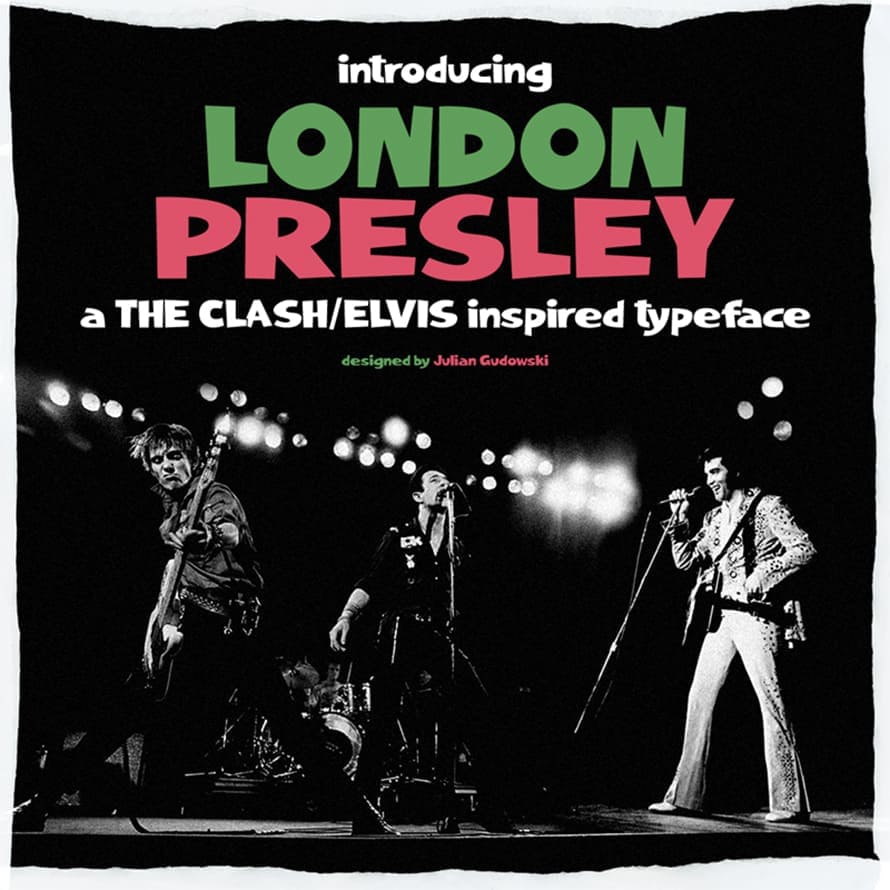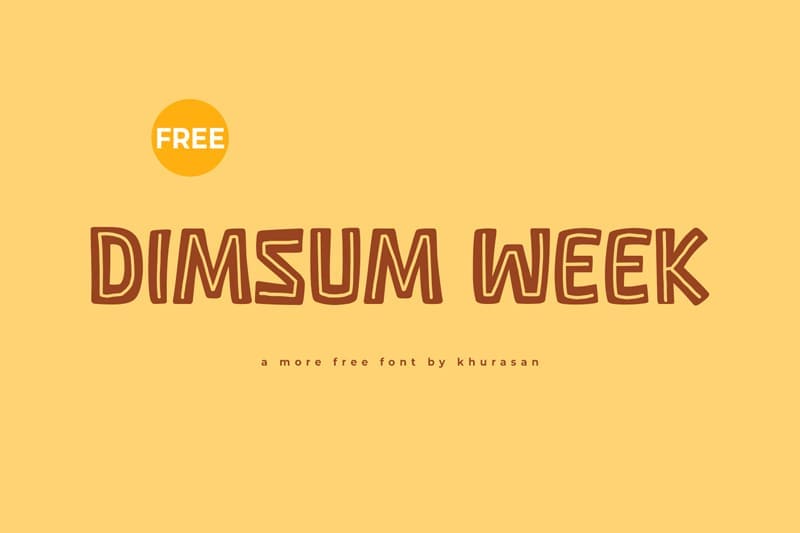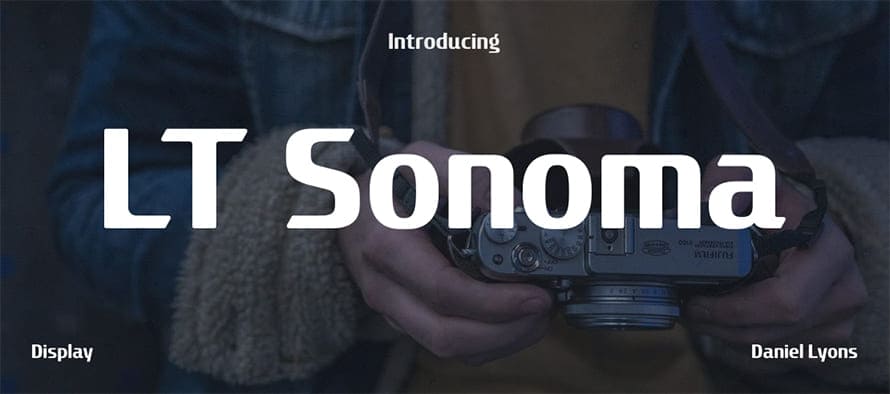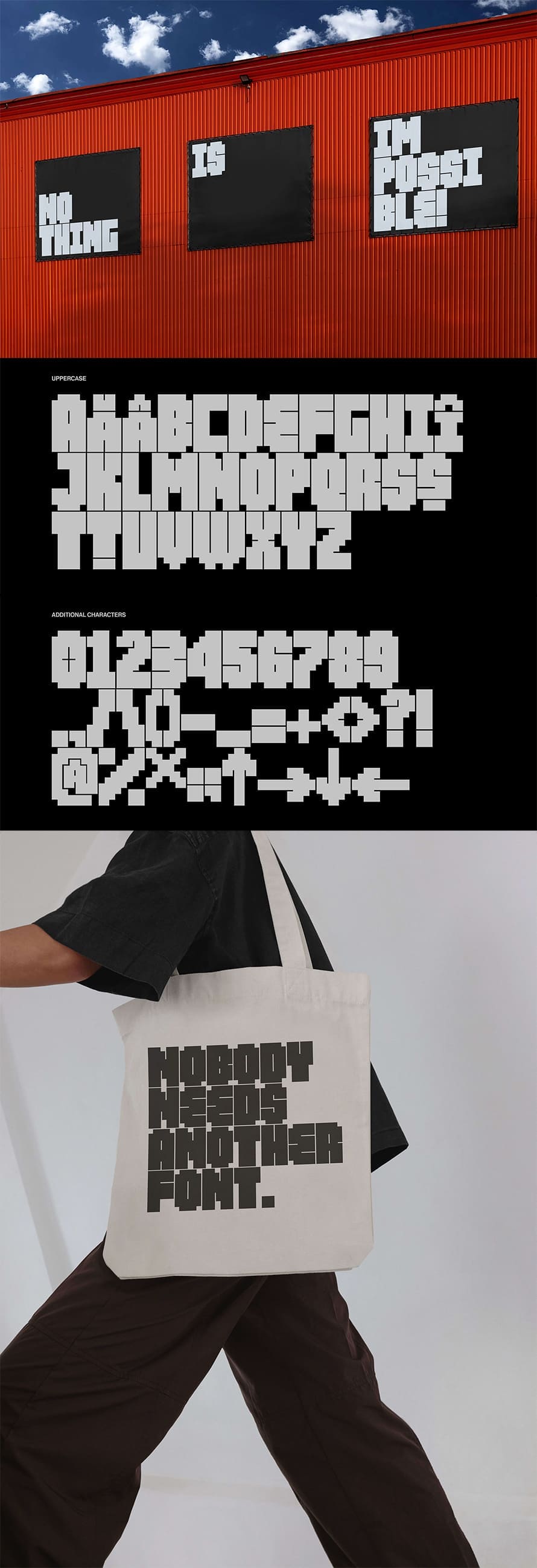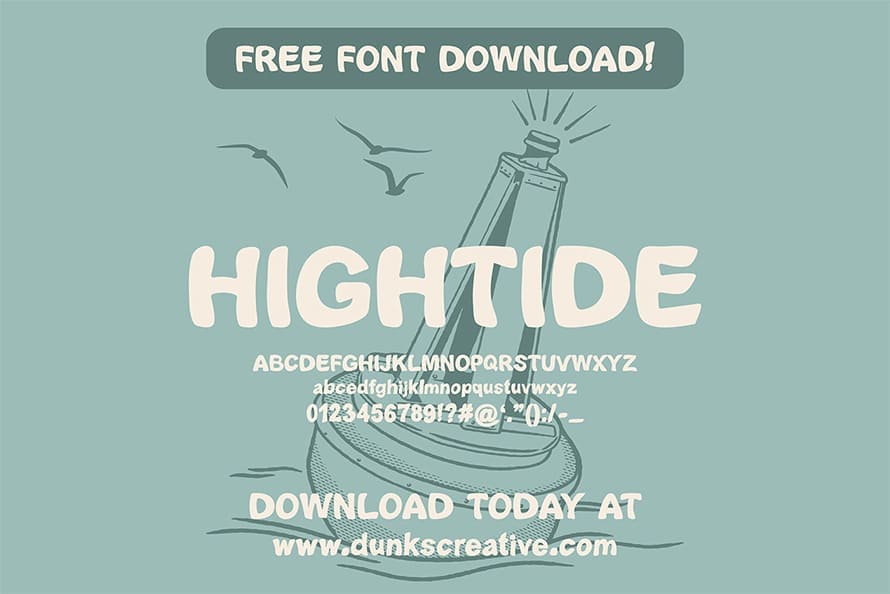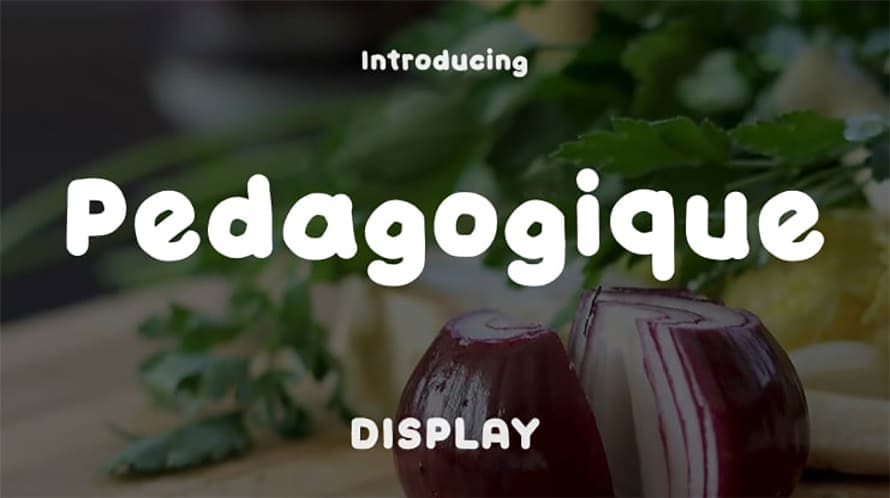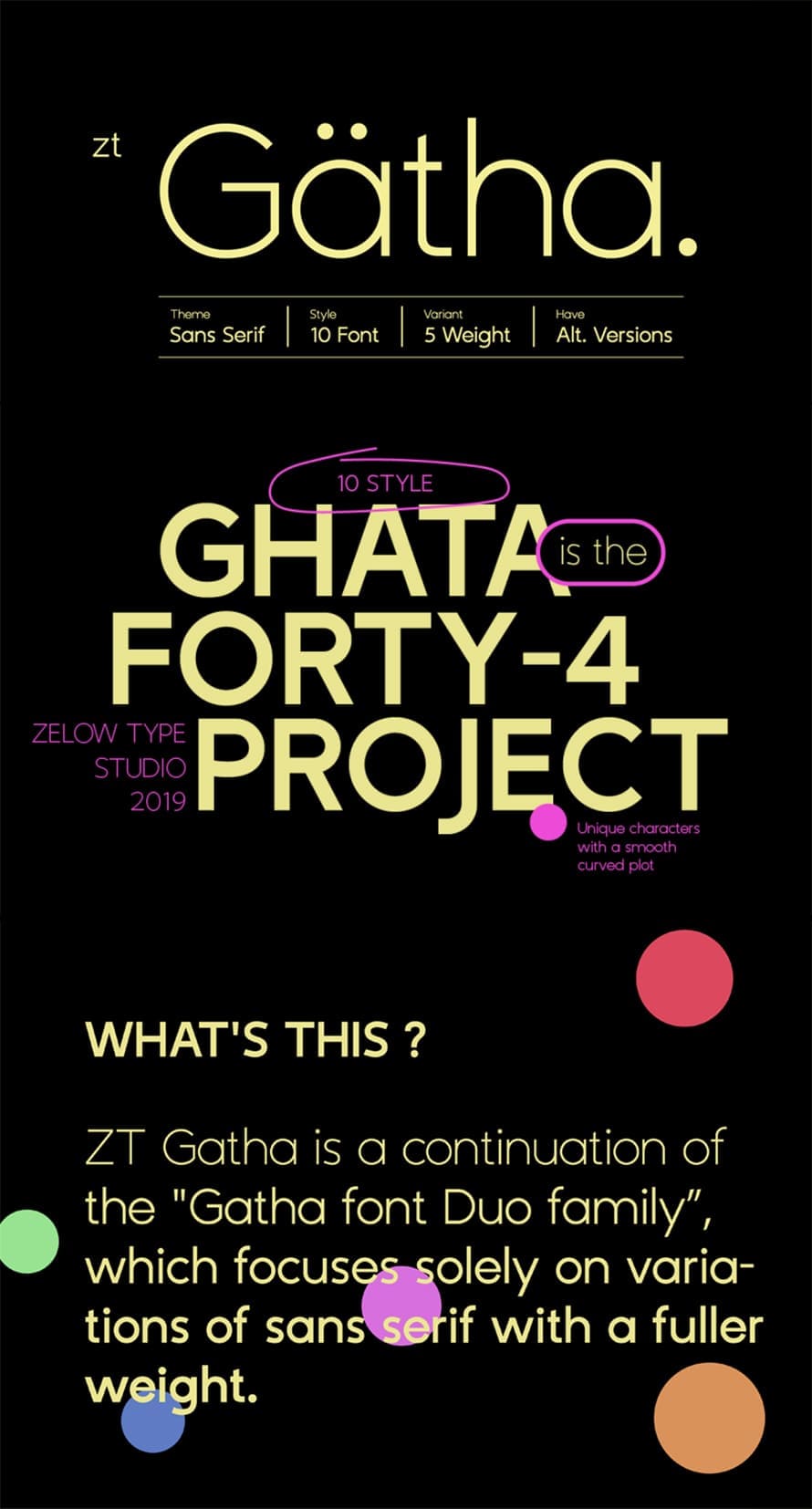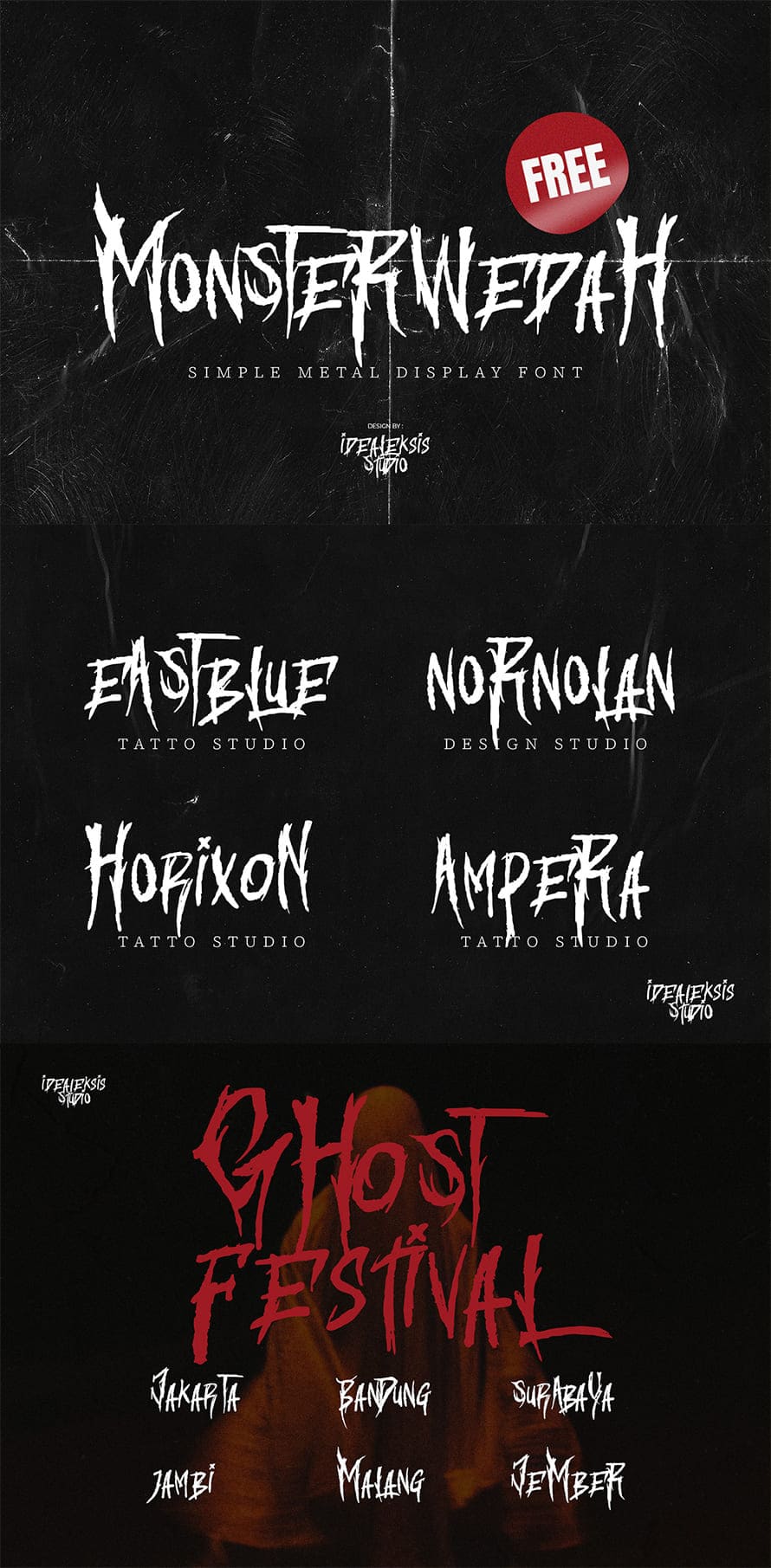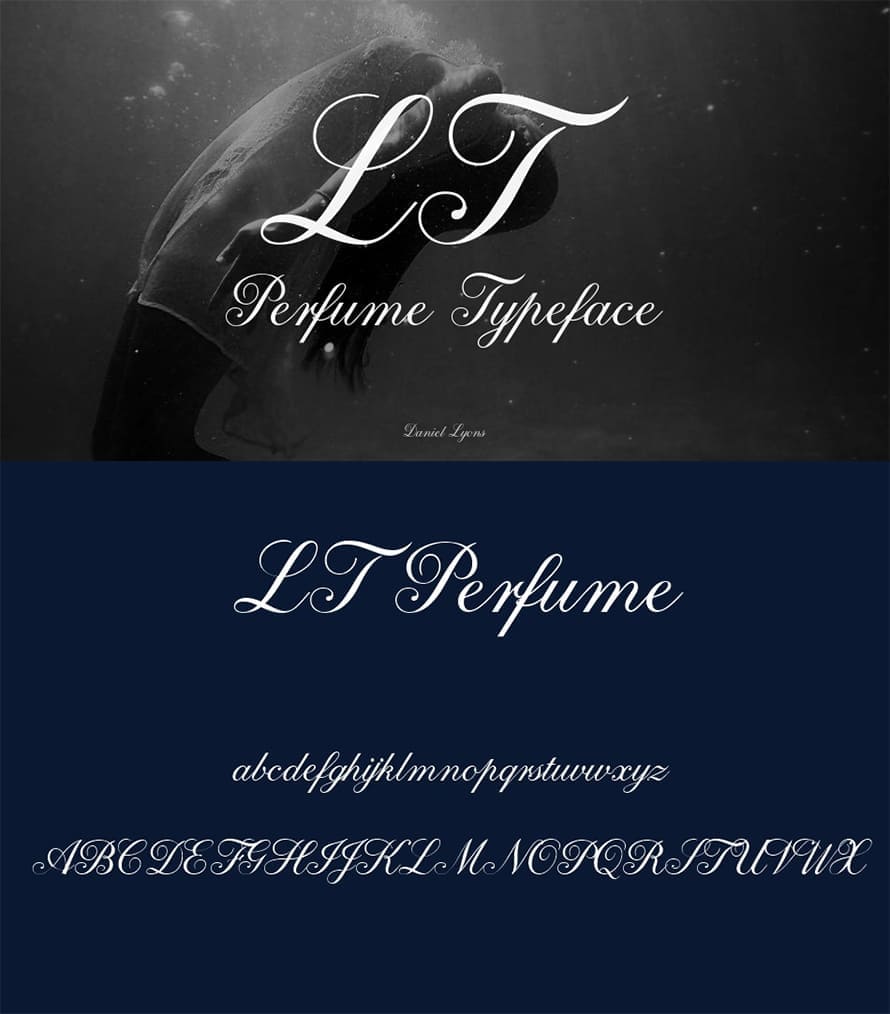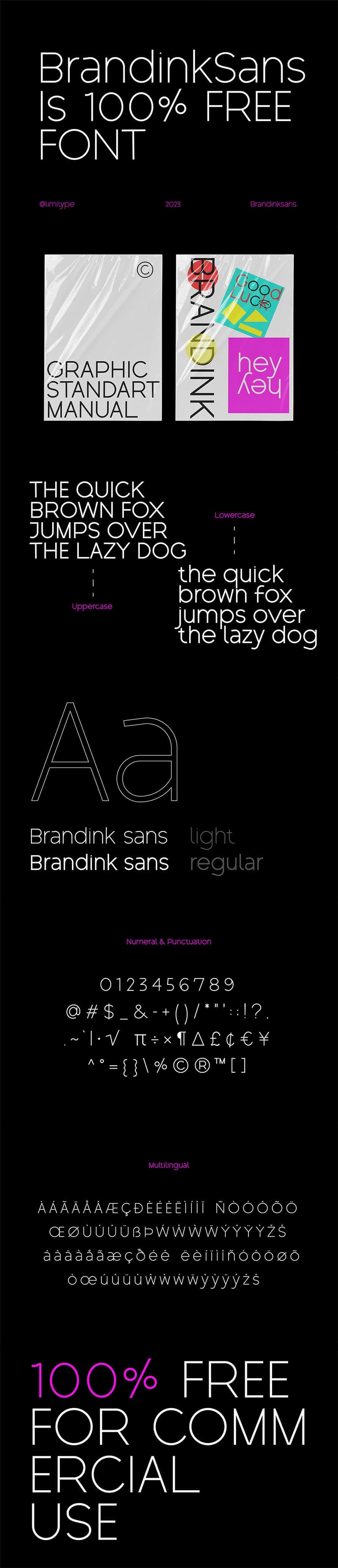
25+ Free Fonts für Designprojekte
In der Welt des Grafikdesigns ist die Suche nach frischen Schriftarten endlos. Designer, sowohl erfahrene als auch Anfänger, sind ständig auf der Suche nach neuen kostenlosen Schriftarten, um ihren Projekten Vitalität zu verleihen. Die Bedeutung der Typografie bei der Übermittlung von Botschaften, beim Hervorrufen von Emotionen und beim Aufbau einer Markenidentität ist nicht zu überschätzen. Daher hat die Verfügbarkeit hochwertiger, kostenloser Schriftarten einen immensen Wert für Designer weltweit.
In diesem Artikel begeben wir uns auf eine Reise, um zu erkunden, wie die Integration der neuesten kostenlosen Schriftarten Ihre Designs zu neuen Höhen der Kreativität und Wirkung führen kann.
Sie befinden sich mitten in einem Designprojekt und suchen nach der perfekten Schriftart, um die Essenz Ihres Konzepts einzufangen. Die Suche beginnt damit, unzählige Schriftartenbibliotheken zu durchsuchen, in der Hoffnung, auf etwas zu stoßen, das mit Ihrer Vision übereinstimmt. Hier kommt die Magie neuer kostenloser Schriftarten ins Spiel. Diese Schriftarten, frisch geprägt von talentierten Designern und Typografen, bieten eine frische Brise inmitten des Ozeans von allgegenwärtigen Schriftarten.
Mit ihren einzigartigen Stilen, innovativen Funktionen und zeitgemäßen Ästhetik bringen neue kostenlose Schriftarten eine Prise Neuheit und Aufregung in Ihre Designvorhaben.
Liste der frischen Schriftarten:
Kreativität mit Vielfalt beflügeln
Als Designer gedeihen wir auf Inspiration, und nichts entfacht unsere Kreativität so sehr wie das Entdecken einer faszinierenden neuen kostenlosen Schriftart. Jede Schriftart erzählt eine Geschichte, die die kreative Vision und die akribische Handwerkskunst ihres Schöpfers widerspiegelt. Von schlanken serifenlosen Schriften bis hin zu eleganten Serifen, eigenartigen Display-Schriften bis hin zu vielseitigen Skript-Stilen – die Vielfalt neuer kostenloser Schriftarten stellt sicher, dass es für jedes Projekt und jede Vorliebe etwas Passendes gibt.
Ob Sie eine elegante Unternehmensbroschüre gestalten, ein verspieltes Poster entwerfen oder eine herausragende Markenidentität entwickeln, die richtige Schriftart kann den Unterschied ausmachen.
Frische Schriftarten: Erheben Sie Ihre Designs mit den neuesten kostenlosen Schriftarten
Die Schönheit von frischen Schriftarten liegt nicht nur in ihrer visuellen Anziehungskraft, sondern auch in ihrer Zugänglichkeit. In einer Welt, in der Designressourcen oft mit hohen Preisschildern verbunden sind, dienen kostenlose Schriftarten als Leuchtfeuer der Inklusivität, die das Design demokratisieren und Schöpfer aus allen Lebensbereichen befähigen. Mit nur wenigen Klicks können Designer diese Schriftarten herunterladen und in ihre Projekte integrieren und damit ihr kreatives Potenzial entfesseln, ohne das Budget zu sprengen.
Diese Zugänglichkeit fördert eine Kultur der Zusammenarbeit und Innovation, in der Designer ihre Kreationen frei teilen zum Wohl der Gemeinschaft.
Lassen Sie uns die neueste Auswahl von über 25 kostenlosen frischen Schriftarten entdecken, die perfekt für kommerzielle Projekte geeignet sind.
Ortland Kostenlose Schriftart
Die Crooker Schriftart
Bion Kostenlose Schriftart
Bion Kostenlose Schrift art
Lokanova Kostenlose Schriftart
Dimsum Woche Kostenlose Schriftart
London Presley Kostenlose Schriftart
Simple Daily Kostenlose Schriftart
Block Free font
LT Sonoma Kostenlose Schriftart
Beyne Kostenlose Schriftart
Gemes Kostenlose Schriftart
Tradde Issue Kostenlose Schriftart
LT Perfume Kostenlose Schriftart
LT Perf ume Kostenlose Schriftart
HighTide Kostenlose Schriftart
Transforma Script Kostenlose Schriftart
Monster Wedah Kostenlose Schriftart
Pedagogique Kostenlose Schriftart